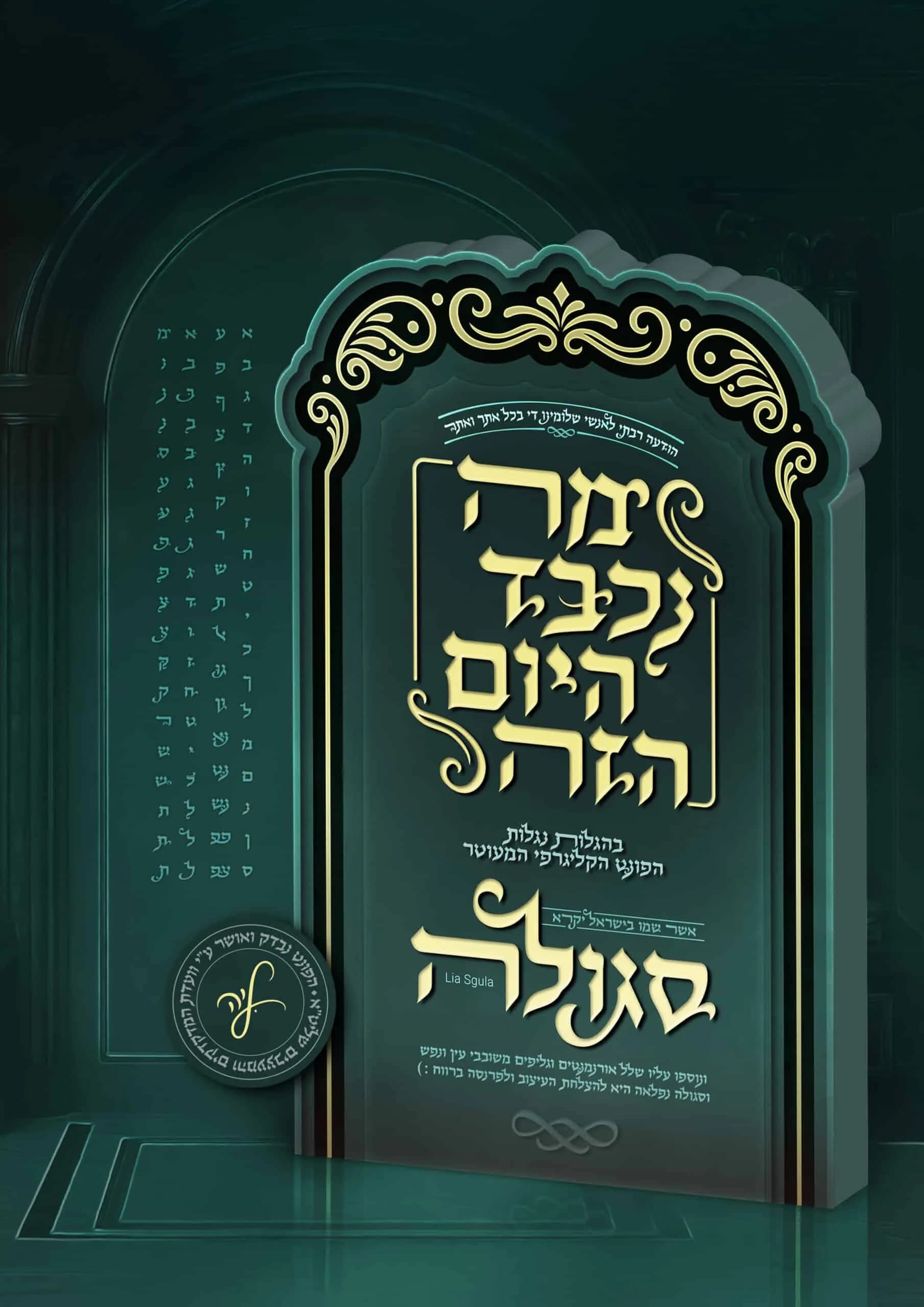
סגולה הוא פונט עברי שנולד מתוך אהבה למסורת הכתיבה היהודית. בהשראת קליגרפיה עברית קלאסית, כרזות ישנות וכתבי קודש, הוא משלב נוכחות מכובדת עם זרימה טבעית וחיה. כל אות עוצבה בקפידה כדי להעניק תחושה אותנטית של כתב יד מסורתי, מבלי להתפשר על קריאות ונוחות בעבודה מודרנית. סגולה מתאים במיוחד להזמנות, ספרי קודש, כריכות, תעודות, פרויקטים קהילתיים, מיתוג בעל אופי יהודי ועיצוב המבקש להעביר עומק, כבוד וחיבור למסורת.